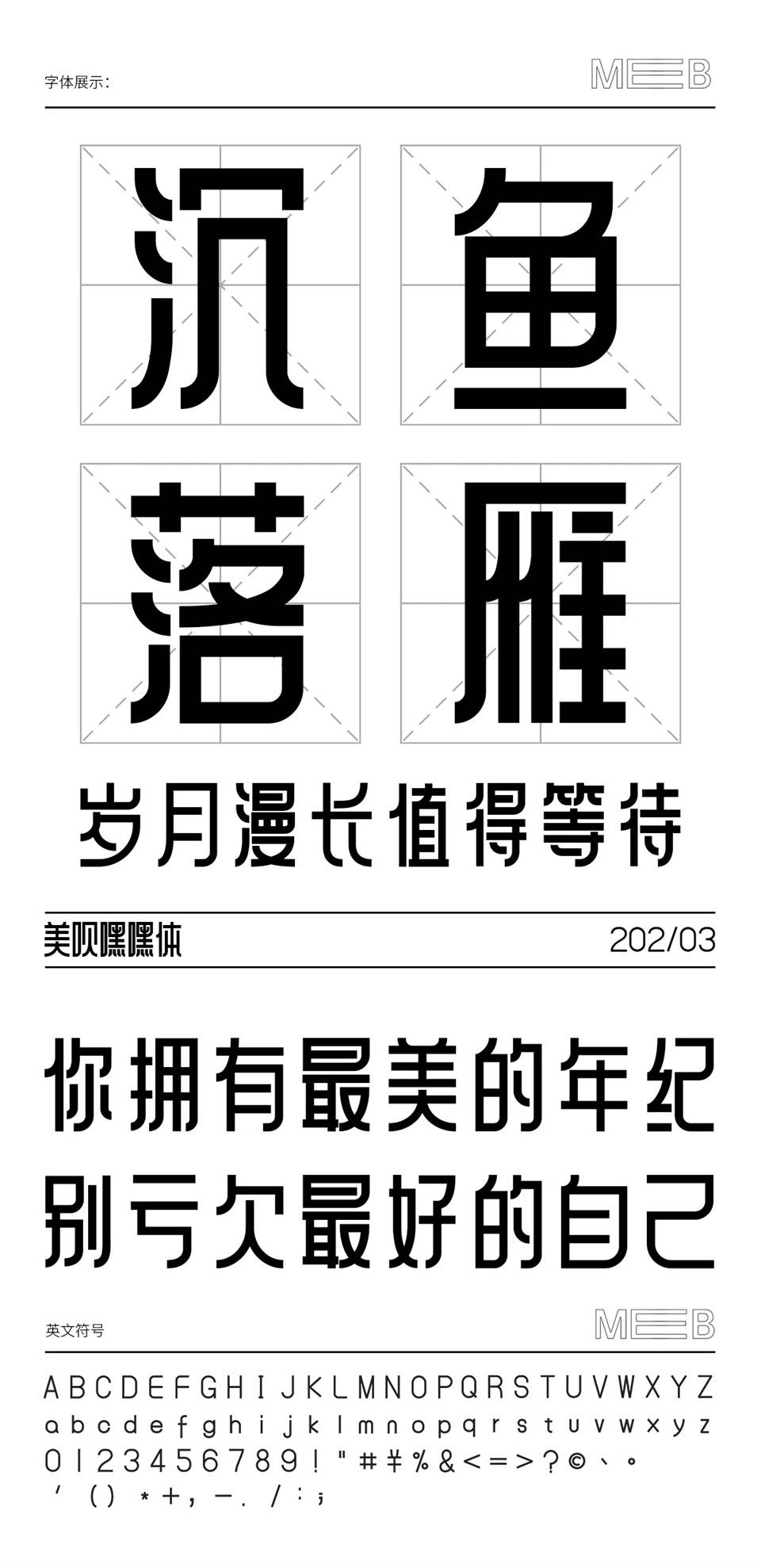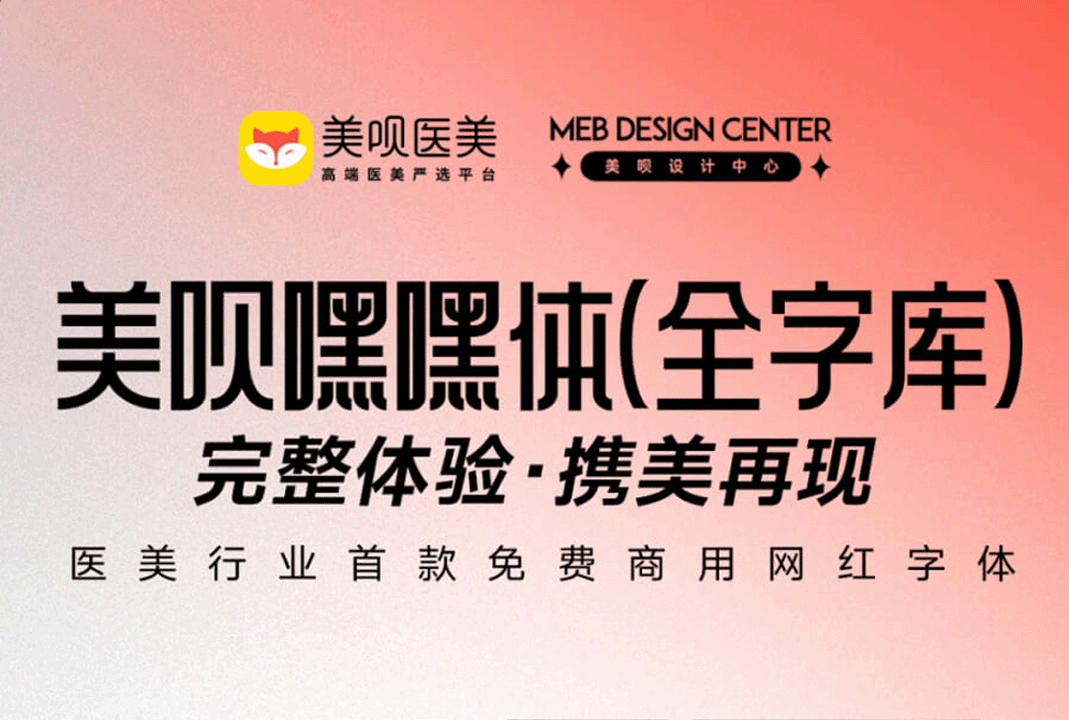
美呗嘿嘿体3.0 | 免费中文商用字体下载
美呗嘿嘿体由美呗设计团队制作,该团队为了让品牌符号更加鲜明、让美呗er更有归属感,他们秉承着“开放、合作、创新“公司价值观推出的一款通用型强的黑体字体,有着时尚、年轻、女性化的气质。美呗嘿嘿体,允许任何个人和企业免费使用。
美呗嘿嘿体3.0全字库符合GB2312简体中文编码字符标准的品牌字体,包含6767个中文字符和150+西文及数字符号。